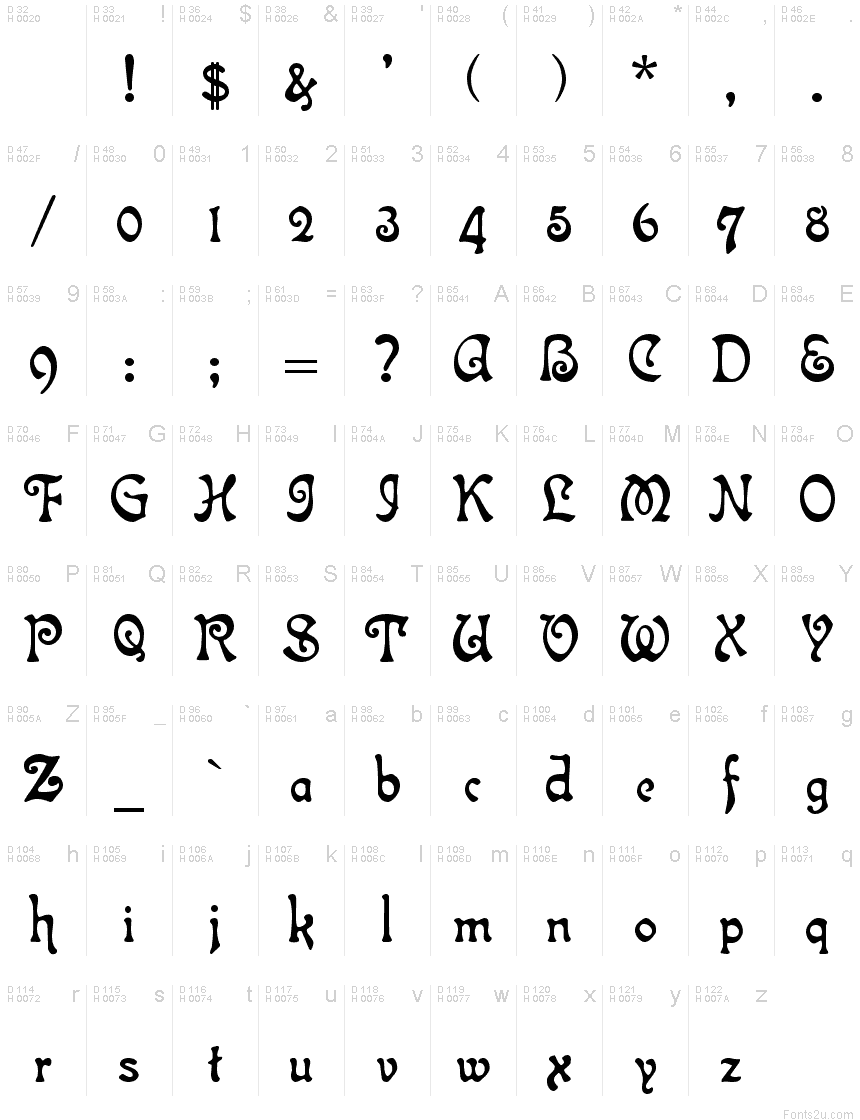
Il font Isla Bella di Blake Haber è un carattere display gratuito in stile retro, dotato di un fascino artigianale meravigliosamente eccentrico. I tratti spessi e densi si trasformano in curve morbide, mentre le grandi terminazioni a spirale ricordano le onde che si infrangono su un'insegna da spiaggia. Le lettere presentano un leggero tremolio che le rende vive e solari, come se fossero state dipinte a pennello sul legno e lasciate asciugare nella brezza salmastra.
Con Isla Bella, puoi donare un calore giocoso e leggermente psichedelico a poster, menu di beach bar, branding a tema surf o tiki, inviti per feste di bambini, packaging e titoli di eventi. Questo font gratuito brilla particolarmente nelle grandi dimensioni, dove i suoi riccioli e le sue spirali corpose possono davvero respirare. Abbinalo a un sans serif geometrico pulito per il testo principale, così da mantenere la leggibilità, mentre Isla Bella si occuperà di tutta l'energia divertente dei titoli.